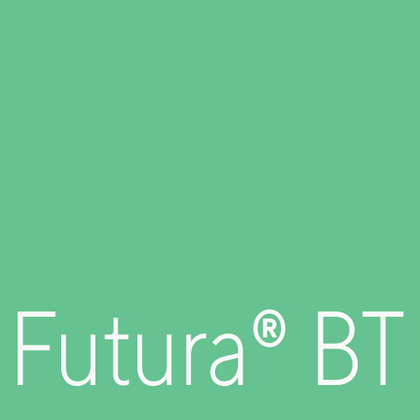
Fuentes similares a Futura BT
Para proyectos donde un estilo geométrico claro es importante, tenemos excelentes alternativas. Futura® BT es una buena opción, pero en la colección de TypeType encontrarás soluciones con soporte cirílico. Son ideales para cualquier tipo de proyecto, desde logotipos hasta sitios web.
Elige entre numerosas opciones de peso y crea diseños con estilo, sin limitaciones.
Si estás cansado de las fuentes desgastadas y busca tipos de letra similares a Futura BT, consulta nuestras principales alternativas a Futura BT. Estas son fuentes que tienen características similares, pero al mismo tiempo tienen características de diseño nuevas y únicas. Por ejemplo, pertenecen a la misma categoría de fuentes, son adecuadas para los mismos fines y tienen características similares, pero difieren en detalles o proporciones.
En TypeType encontrarás fuentes de vanguardia, tales como Futura BT e incluso mejores: aquí hay algunas alternativas excelentes y menos comunes a Futura BT. Utiliza esta lista de fuentes de alta calidad con apariencia Futura BT que se adapten a tus gustos. De esta manera podrás elegir una fuente aún más adecuada para tu proyecto, ampliar la selección o actualizar tu diseño. Todas las fuentes que aparecen en esta colección están disponibles en diferentes formatos y a precios asequibles, por lo que podrás encontrar una que se adapte a cada necesidad.
Encuentra un excelente reemplazo para Futura BT e intenta emular un estado de ánimo similar usándolo en sus diseños. Cada fuente presentada en esta página es un doble de la fuente Futura BT, de hecho, su análogo completo.
TT Fors es una navaja suiza del diseño tipográfico. Esta sans serif geométrica ofrece una versatilidad absoluta gracias a sus proporciones limpias y refinadas. Puede utilizarse tanto para definir interfaces como para crear acentos visuales.